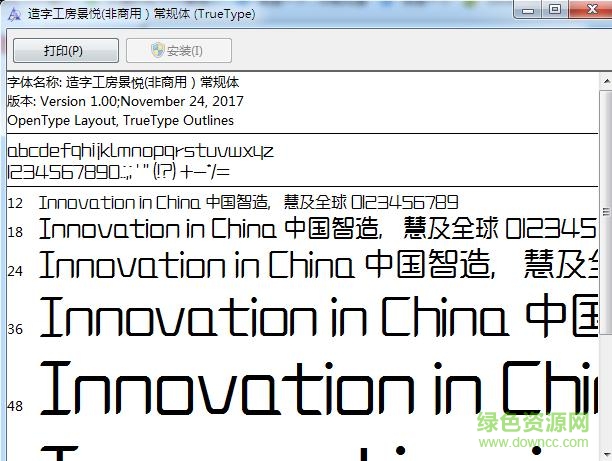
造字工房景悅
造字工房景悅字體是一款全新的電腦字體,給人非常正式有勁的感覺,字體整體效果比較醒目,適合用來作為標(biāo)題使用,有需要的朋友歡迎下載!
造字工房景悅字體簡介
造字工房景悅字體是造字工房全新打造的一款中文字體,筆畫挺勁、秀美,點(diǎn)的圓潤處理猶如雨點(diǎn)墜落,跟撇、豎的尖角處理相結(jié)合,讓字體更加清晰雅致、個(gè)性鮮明。